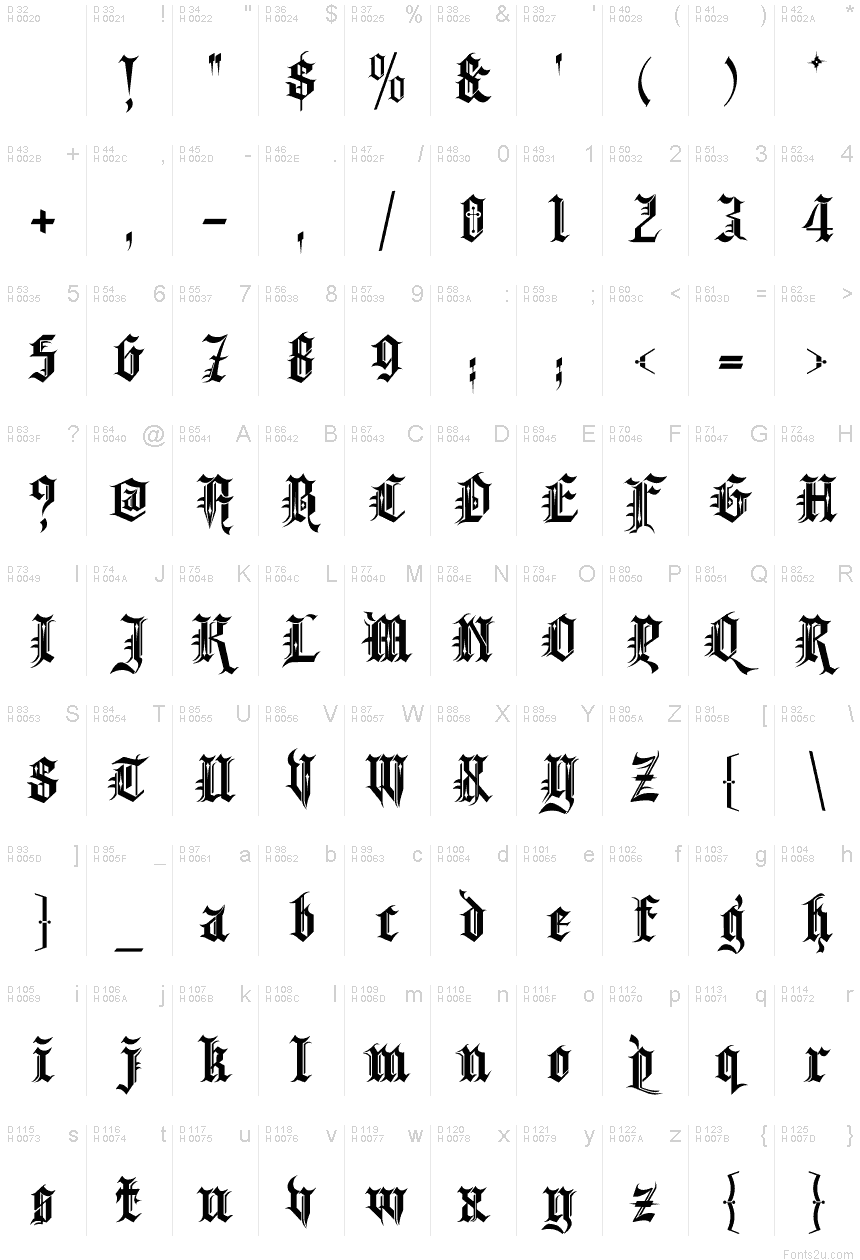
Kingthings Spikeless
Kevin King
Kingthings 的 Kingthings Spikeless 是一款免费的哥特体字体,带有中世纪书法强烈的戏剧张力。高大、结构紧凑的字母将宽粗的竖笔画与细腻的切口和尖锐的接笔结合在一起。舒展的起笔和分叉的花体赋予了字形华丽且近乎纹章般的剪影。
它可以为奇幻游戏、历史活动或金属乐队专辑封面创作出具有戏剧效果的标题。严谨的角度也适合带有复古或神秘主义风格的酿酒厂品牌设计和周边商品。在这些用途中,文字排版既是文本又是徽章,其重复的尖刺、深沉的体量和书法般的装饰将排版与盾徽、武器及其他受时代启发的意象紧密联系在一起。